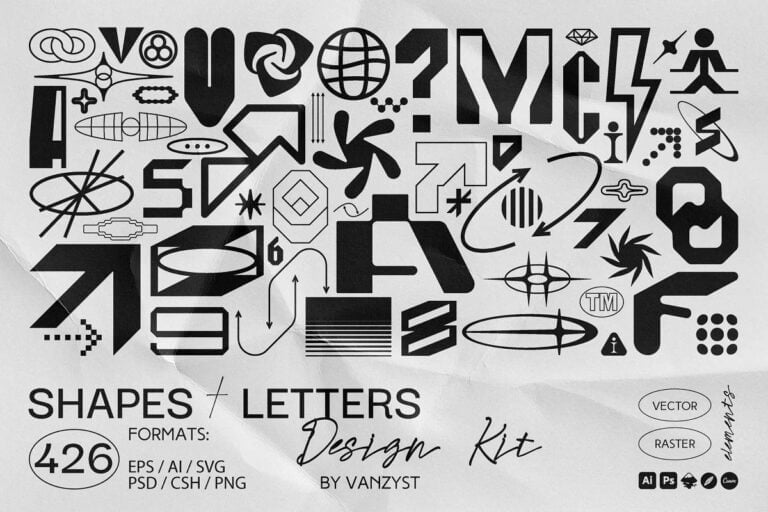
Bộ công cụ chất lượng cao này được lấy cảm hứng từ xu hướng kiểu chữ hiện đại. Typography là một trong những phần có giá trị nhất trong thiết kế đồ họa, các hình khối có thể đan xen hài hòa với các chữ trang trí cũng không kém phần quan trọng. Trong dự án này, bạn sẽ tìm thấy bộ sưu tập phong phú nhất về các yếu tố thiết kế và chữ in hoa giúp tạo ra nhiều loại sản phẩm.
Dưới đây là Typography logo Kit với ✦ 426 nội dung đồ họa độc đáo ✦ bao gồm 322 Hình dạng Hình học, 104 Chữ cái và Số (bảng chữ cái đầy đủ với nhiều tùy chọn chữ cái) dành cho thiết kế poster Hợp thời trang, Logo, tạo Quần áo in theo yêu cầu, nhãn hiệu thời trang dạo phố, mạng xã hội, bài đăng, thiết kế package và hơn thế nữa.